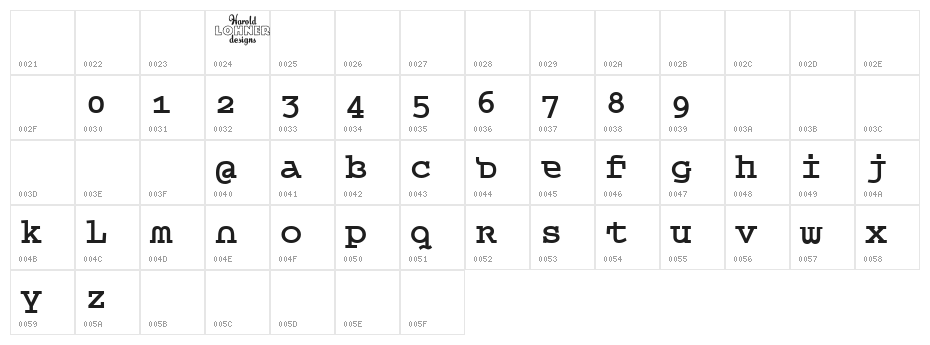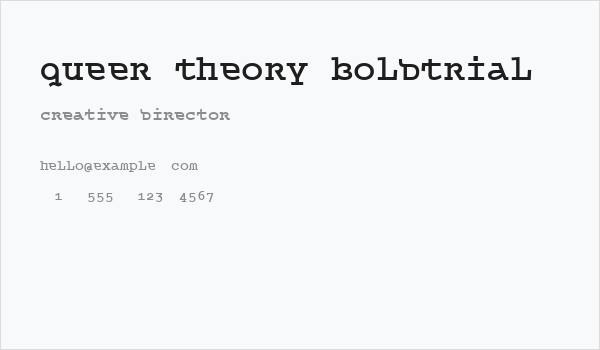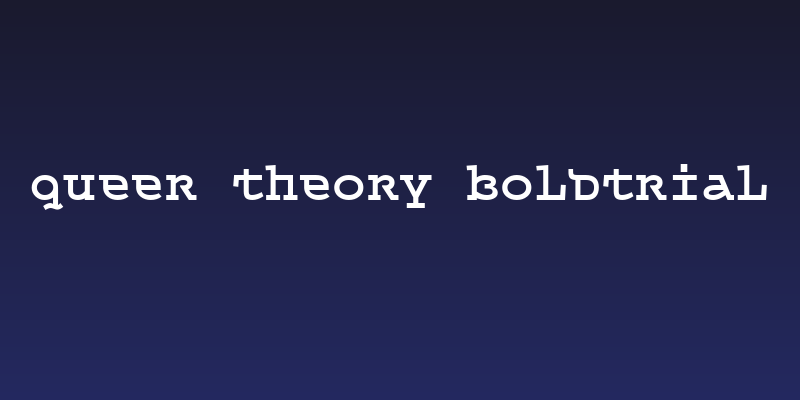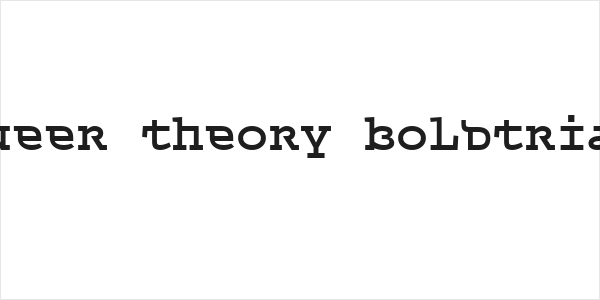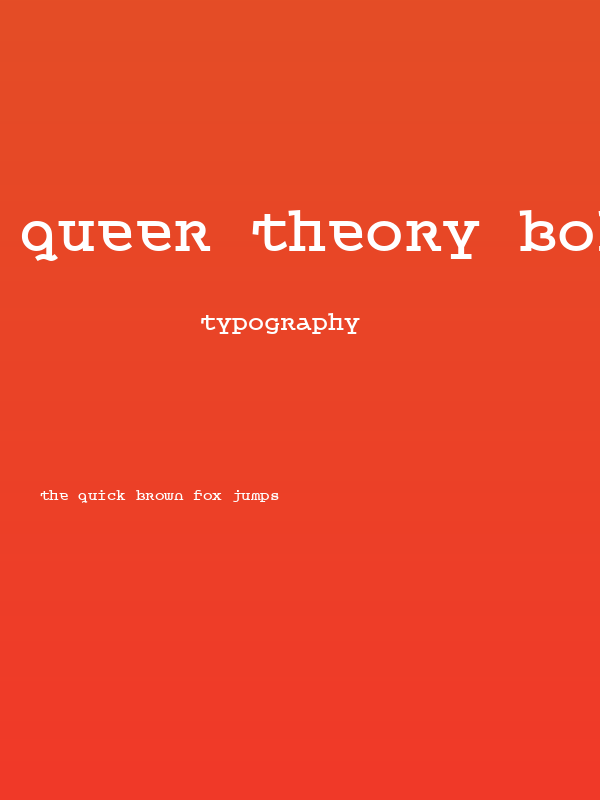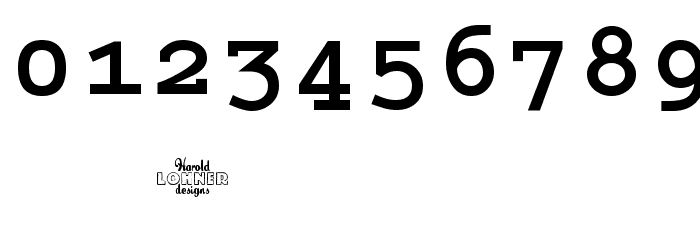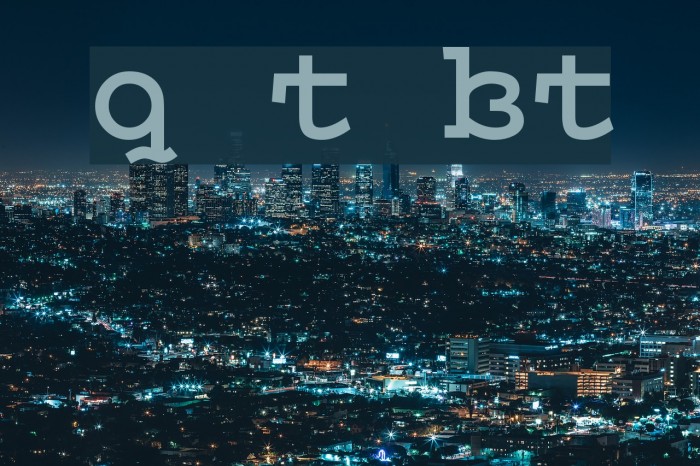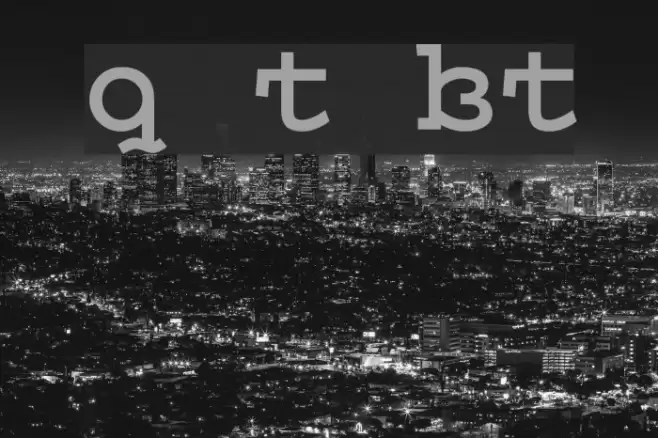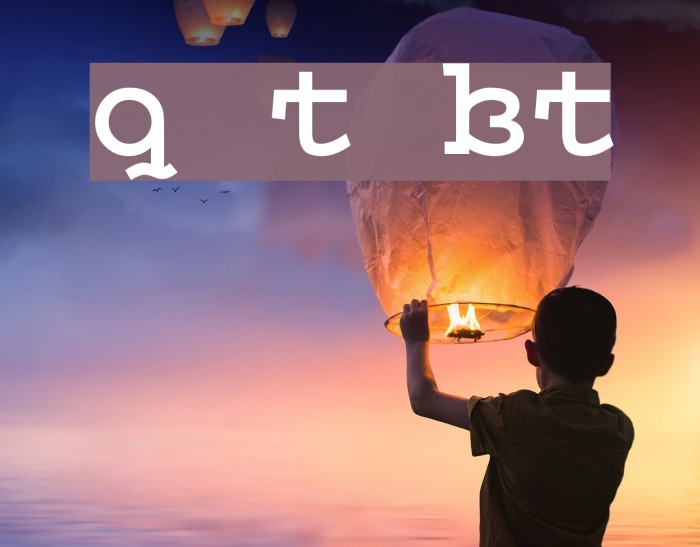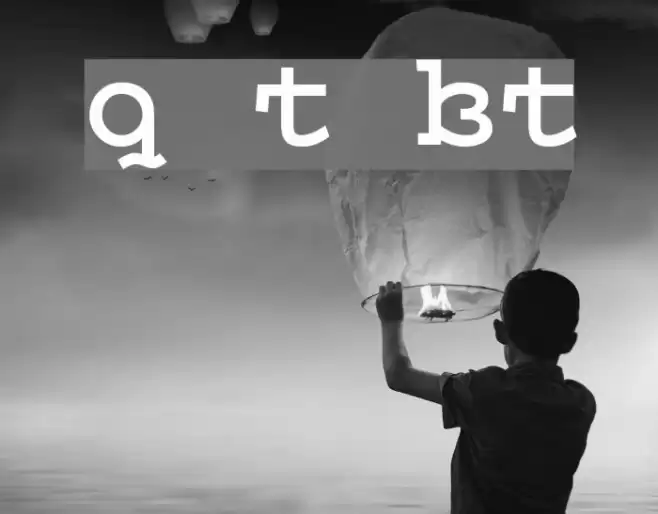
Queer Theory BoldTrial Font
| Gesamtstil | Playful, Quirky |
| Vorgeschlagene Projekte | Ideal for branding, posters, children's books, and any project requiring a whimsical touch. |